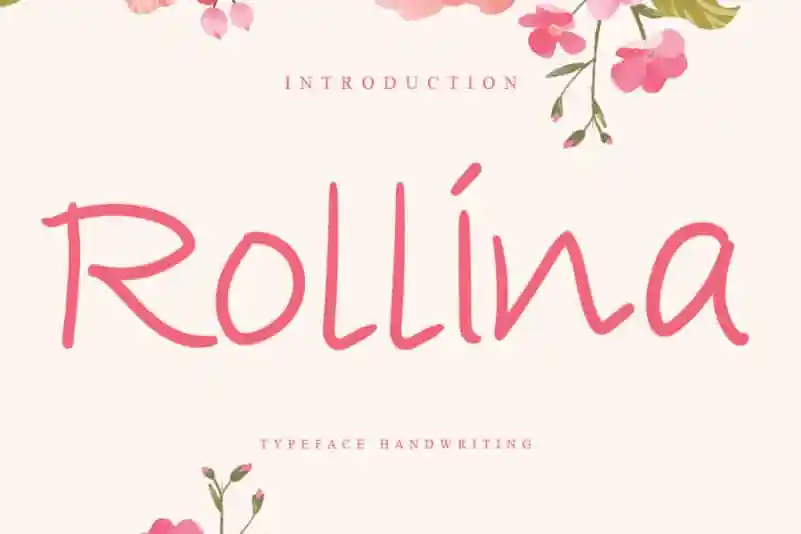
A Rollina Handwritten Font é uma delicada e agradável fonte escrita à mão, com um estilo moderno e versátil. Sua personalidade elegante faz dela uma escolha ideal para uma ampla variedade de projetos gráficos, desde identidades corporativas até designs criados para casamentos, convites, assinaturas, logotipos, etiquetas — e muito mais! Suas linhas suaves e seu aspecto contemporâneo o tornam perfeito tanto para estilos tradicionais quanto para tendências modernas. A Rollina é a escolha ideal para quem procura uma fonte escrita à mão que não apenas complementa suas idéias de design, mas as eleva ao próximo nível. Ela promete dar um toque único e personalizado a qualquer projeto gráfico em sua categoria.